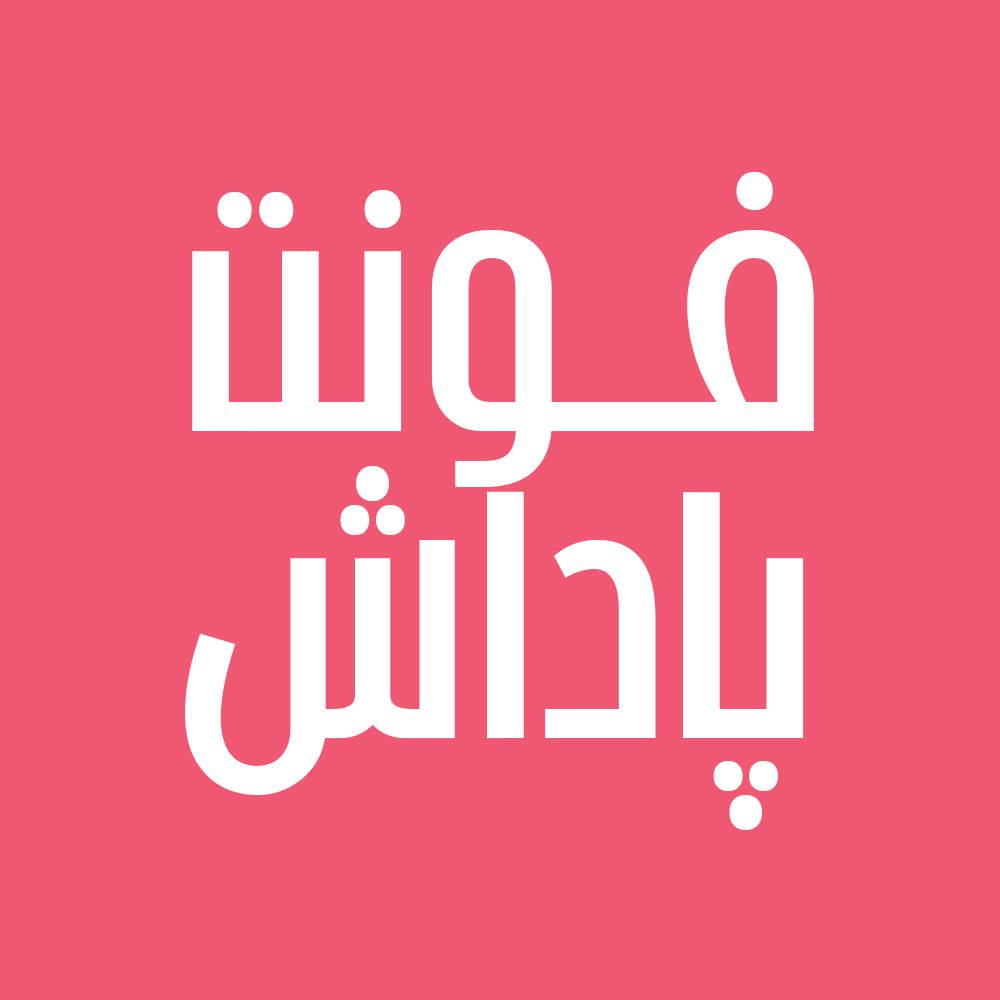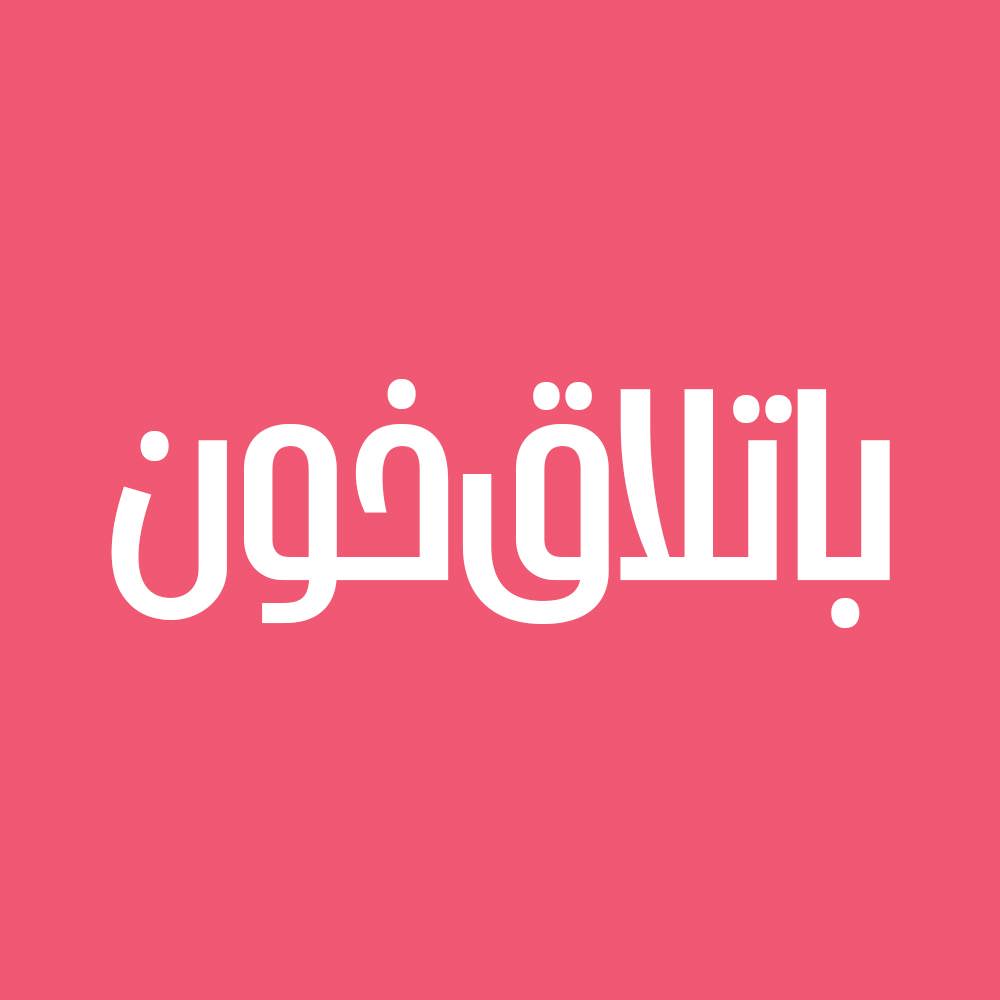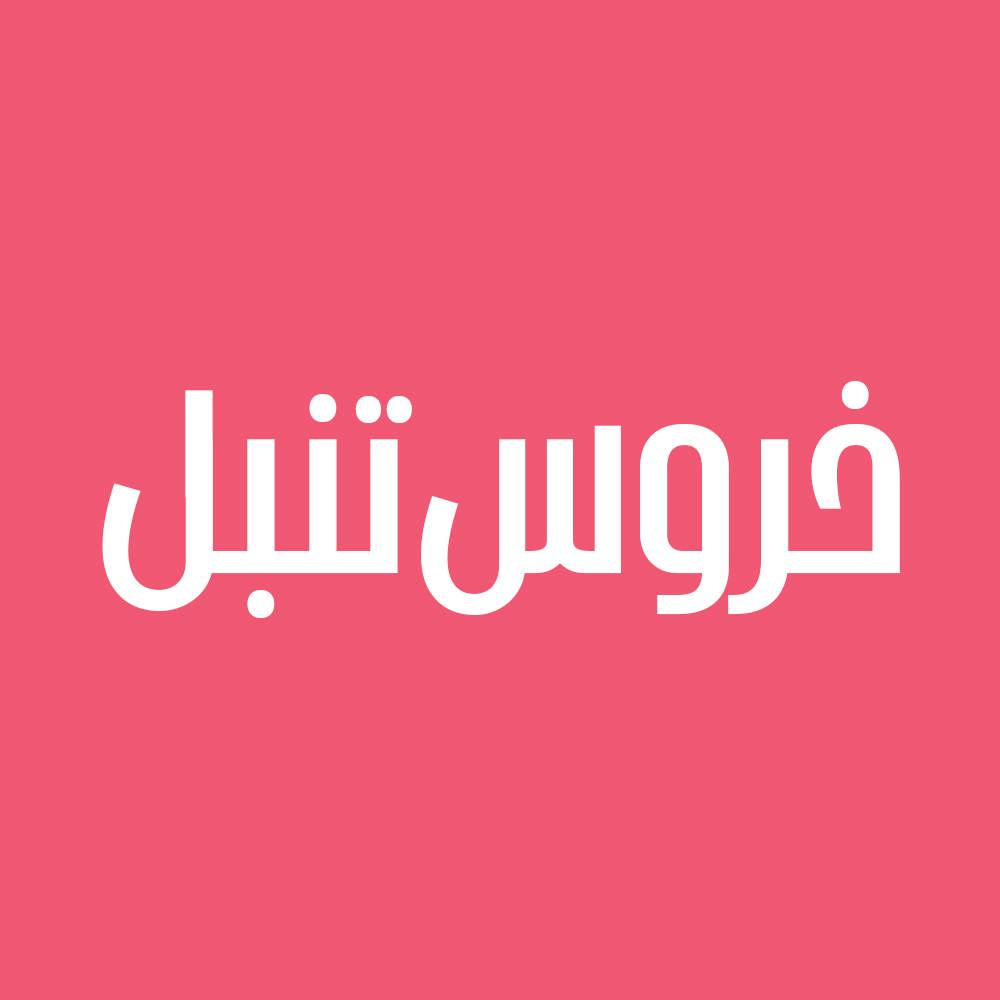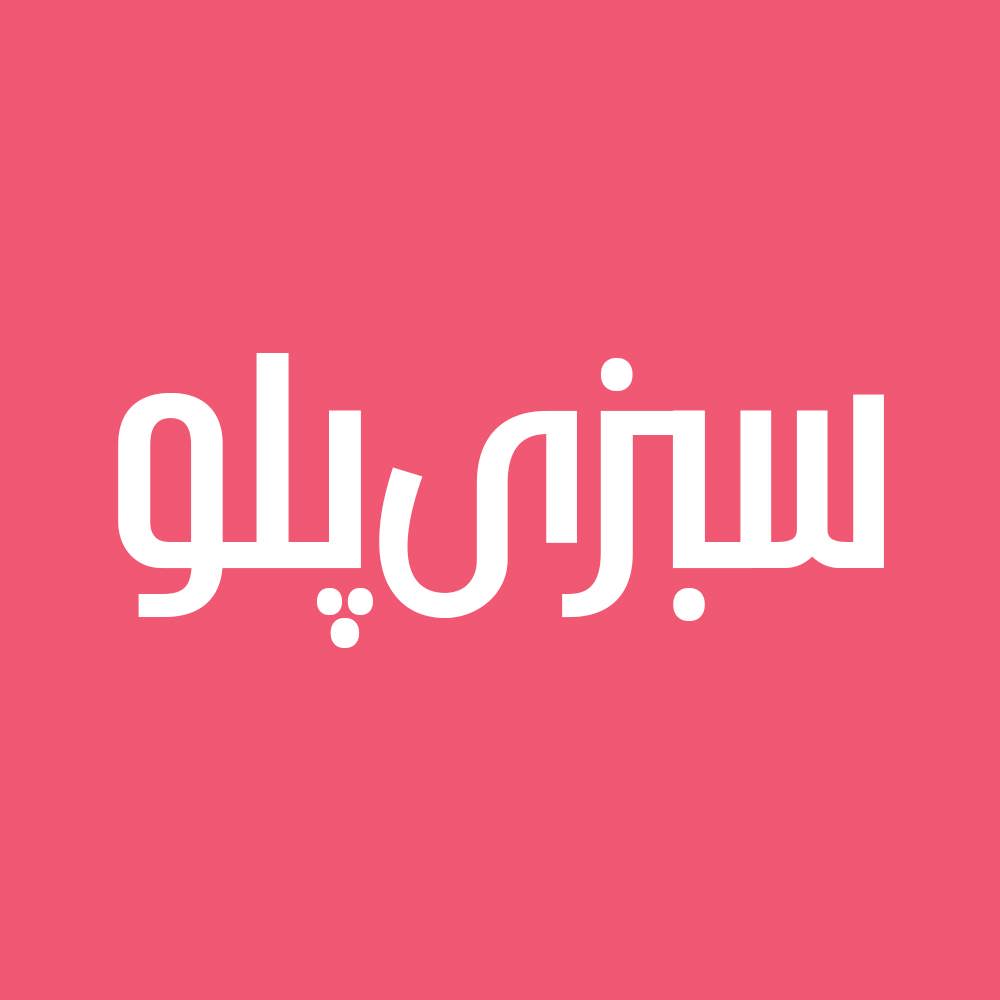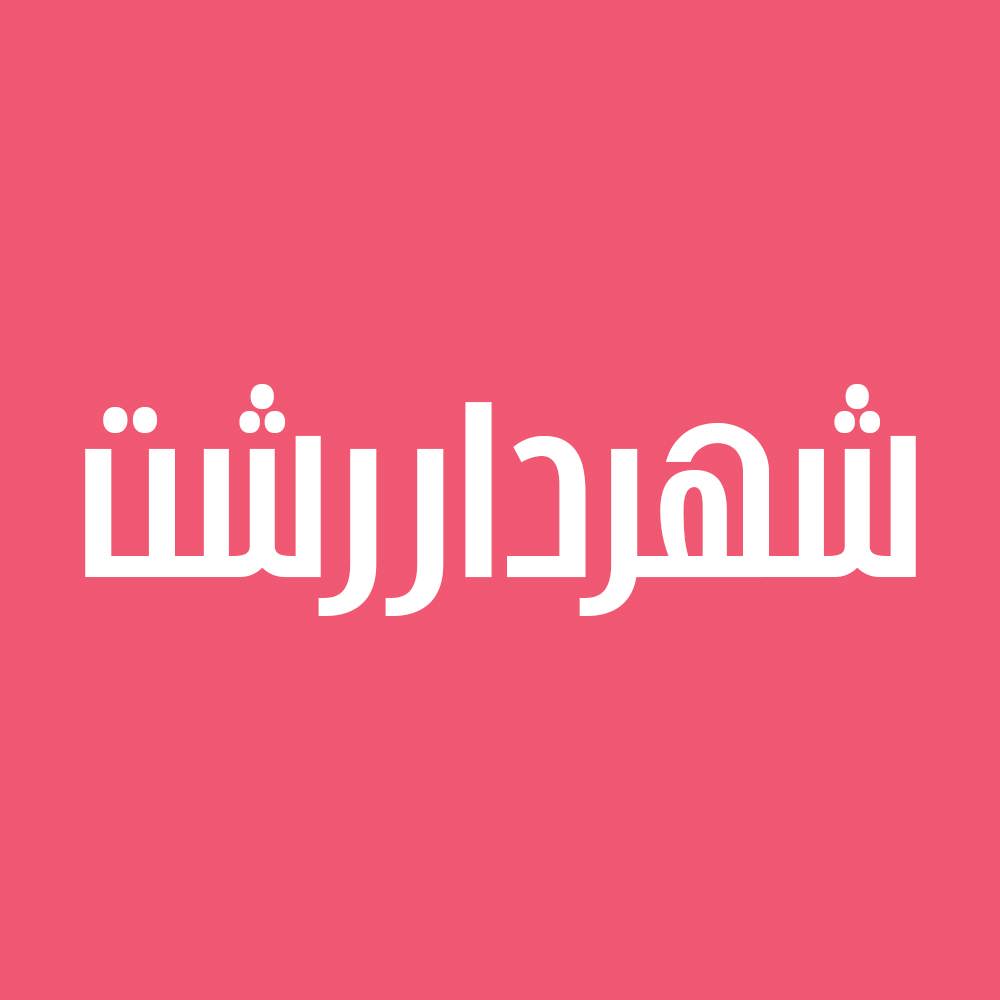
فونت فارسی پاداش Padash Font
فونت فارسی پاداش یک فونت تک وزن با کاربرد طراحی لوگوتایپ و طراحی های مختلف همچون کتاب و تولید محتوای متن های کوتاه و عناوین می…
فونت فارسی پاداش یک فونت تک وزن با کاربرد طراحی لوگوتایپ و طراحی های مختلف همچون کتاب و تولید محتوای متن های کوتاه و عناوین می باشد. این فونت با ساختار حروف خود مناسب استفاده در لوگوهای نوشتاری می باشد. فونت پاداش با تعادل عادلانه ای که بین شکل انسانی حروف و جنبه هندسی آن ترکیب می کند، به ویژگی کاریزماتیک خود دست می یابد. همچنین از این فونت در طراحی تابلوهای چلنیوم هم به دلیل ساختار منحصر به فردش می توانید استفاده کنید. در ادامه برای شما نمونه تایپ های این محصول حرفه ای رو آماده کردیم که میتونید مشاهده کنید.
• مناسب طراحی بسته بندی ها و چاپ
• فونت ویژه تبلیغات محیطی
• فونت طراحی کاور اینستاگرام
• فونت حرفه ای برای تولید محتوا
• فونت فارسی طراحی وبسایت
• فونت طراحی لوگو تایپ فارسی
• مناسب استفاده در تابلو های چلنیوم و طراحی حروف